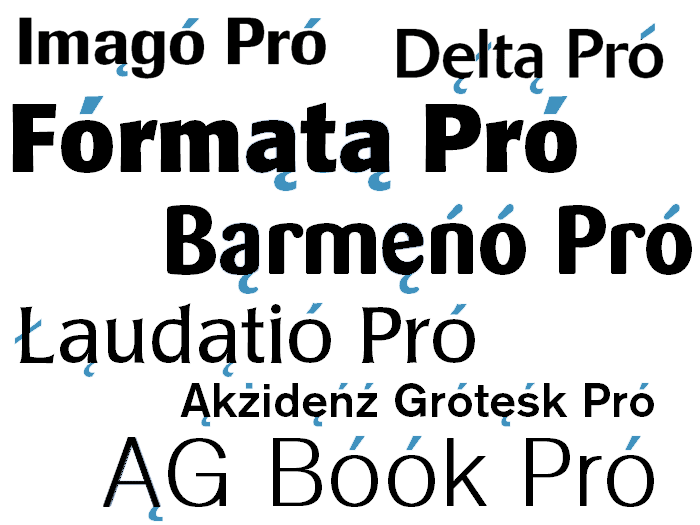
Odlewnia czcionek H. Berthold, znana z wytwarzania wysokiej jakości krojów pism, została założona w 1858 roku w Berlinie przez Hermanna Bertholda. W 1918 roku odlewnia ta była największą na świecie, z siedzibami w Stuttgarcie, Sankt Petersburgu, Lipsku, Rydze, Budapeszcie i Wiedniu. Po II Wojnie Światowej Berthold aktywnie rozwijał własne urządzenia składu tekstu: w latach pięćdziesiątych, Berthold zaprezentował swoją pierwszą maszynę do fotoskładu - Diatype, a w latach sześćdziesiątych Berthold przedstawił Diatronic, jego pierwszy sterowany klawiaturowo fotoskład do produkcji masowej. Rozwijając przedsiębiorczą aktywność w dziedzinie własnego sprzętu do składu tekstu, Berthold opracowywał wysokiej jakości czcionki. Spośród najbardziej znanych rodzin czcionek produkcji H. Bertholda jest niewątpliwie (wydany w 1896) Akzidenz-Grotesk, zwany ojcem wszystkich czcionek bezszeryfowych.
W XX wieku, Berthold stworzył „Berthold Exklusiv Collection” - kolekcję fontów zaprojektowaną wyłącznie dla Bertholda przez wybitnych projektantów. Günter Gerhard Lange, znany mistrz, zaczął współpracę z Bertholdem mniej więcej w tym samym czasie gdy ten wprowadzał fotoskład. Jako dyrektor artystyczny w latach 1961-1990, Lange był odpowiedzialny za kreatywność, drobiazgowe standardy produkcji oraz dbałość o jakość co znalazło potwierdzenie w każdym z fontów Berthold Exklusivs. W 1991 roku Bernd Möllenstädt zastąpił Langego na stanowisku dyrektora działu czcionek Berthold Exklusiv Collection i kontynuował tradycje Langego podczas kierowania digitalizacją Berthold Exklusivs.
W roku 1997 Berthold Types, firma z Chicago, nabyła wszelkie prawa autorskie, prawa do znaków towarowych i wzorów związanych z Berthold Exklusiv Collection. Aż do śmierci w 2008 roku Günter Gerhard Lange pozostawał jako wyłączny doradca artystyczny dla Berthold Types Limited, gdzie w dalszym ciągu rozwijał i projektował nowe kroje Berthold.
Berthold Types kontynuuje tradycję ....